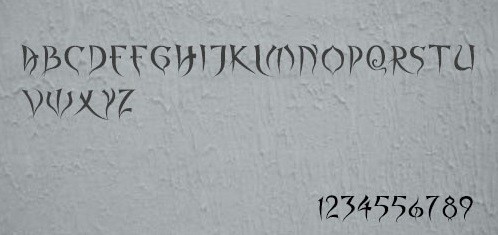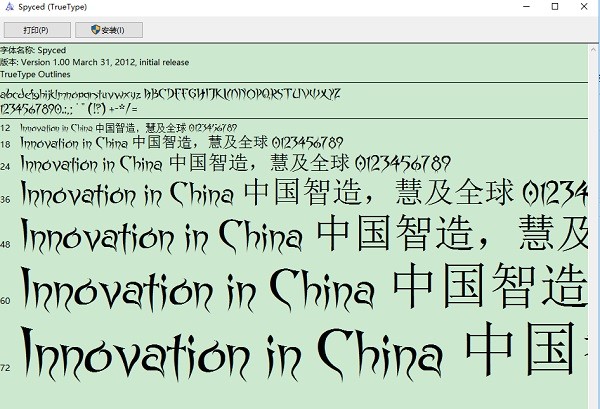
spyced是非常具有哥特式風(fēng)格的藝術(shù)字體,字型在纖細(xì)尤雅的同時(shí),又傳承了哥特式風(fēng)格一貫的灑脫質(zhì)感,非常的復(fù)古和個(gè)性,用于廣告印刷和包裝設(shè)計(jì)非常之醒目,有著非常廣泛的應(yīng)用價(jià)值,喜愛的朋友趕快下載體驗(yàn)吧!